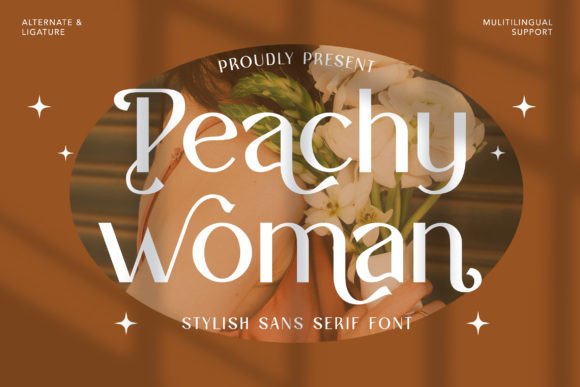
Peachy Woman
適切なデザイン要素を見つけるのは難しい場合がありますが、Peachy Womanは作品を即座に引き立てる優れたコレクションを提供します。
POD(オンデマンド印刷)製品、結婚式の招待状、またはソーシャルメディアのグラフィックを作成している場合でも、Peachy Womanは理想的です。